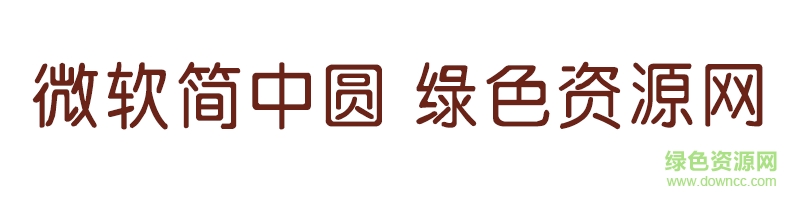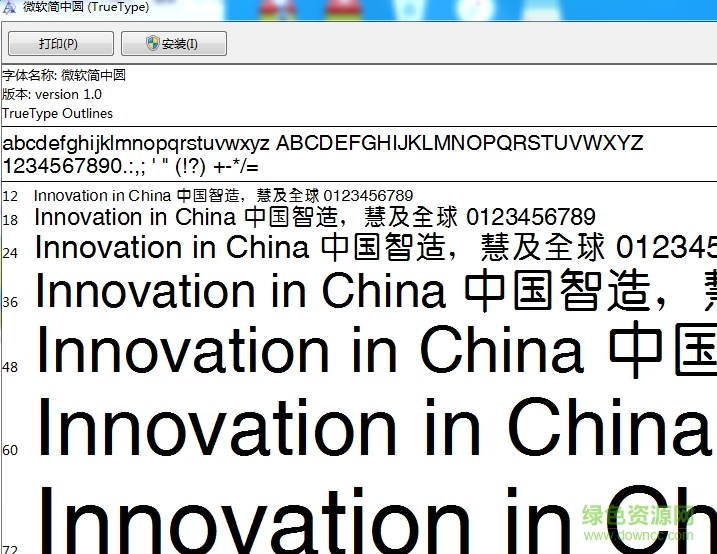
微軟簡(jiǎn)中圓字體是一款微軟字體簡(jiǎn)中圓字體,簡(jiǎn)體中又帶一點(diǎn)圓,微軟字體官方打造,您還在等什么?喜歡就來(lái)綠色資源網(wǎng)下載體驗(yàn)唄!
微軟簡(jiǎn)中圓字體細(xì)致柔順,瘦小的筆觸卻給人剛毅有力的感覺,又不失清秀。是一款非常好看的的字體文件。適合畫冊(cè)正文、報(bào)紙排版、展版設(shè)計(jì)、海報(bào)設(shè)計(jì)等廣告設(shè)計(jì)場(chǎng)合使用。